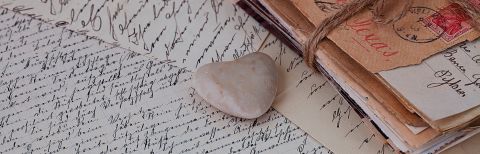
In deutschen Grundschulen und noch mehr in den weiterführenden Schulen liegt der Hauptfokus des handschriftlichen Schreibens in der Lesbarkeit der Schrift und der richtigen Rechtschreibung. Das ist unabdingbar, Lehrkräfte müssen lesen können, was die Schülerinnen und Schüler geschrieben haben, um den Inhalt und die Grammatik bewerten zu können. Die Rechtschreibung dient dazu, Wörter und Sätze eindeutig in ihrer Bedeutung zu machen, so sollen Doppeldeutigkeiten und Interpretationsspielräume ausgeschlossen werden.
Und wenn es beim Schreiben vor allem um Lesbarkeit und Rechtschreibung geht, so werden viele Schülerinnen und Schüler zu Recht fragen, warum sie dann nicht gleich mit dem Computer schreiben dürfen. Garantiert lesbar und eine Autokorrektur für die Rechtschreibung gibt es auch, also warum sollen sie noch mit der Hand schreiben? Die Handschrift hat aber noch weitere Aspekte: Es geht nicht immer nur darum, Inhalte zu vermitteln, sondern auch zu gestalten. Erinnern wir uns an die ersten Bücher, die in Klöstern von Mönchen in mühevoller Handarbeit abgeschrieben wurden, es gab nur einige wenige Exemplare und die waren überaus kunstvoll gestaltet.
Heute gelten sie als Kunstwerke. Briefe und Postkarten werden heute noch mit kleinen Randzeichnungen versehen und auch Bücher werden heute noch teilweise aufwendig illustriert. In diesen Bereichen verschwimmen auch bei uns Schrift und Kunst ineinander. Wer schreibt, gestaltet auch. Es ist durchaus möglich, Emotionen in der Schrift zu lesen. Ob ich einen Liebesbrief schreibe oder einen Einkaufszettel, würde man vermutlich auch an der Schrift erkennen: Meine Handschrift ändert sich, wenn ich schnell, energisch, nachdenklich oder wütend schreibe. Und manchmal werden uns Emotionen erst beim Schreiben bewusst, denn dann schreibt man in einem „Fluss“, das heißt, die Gedanken – positive wie negative – strömen vom Kopf wie von selbst über den Stift zum Papier. Das ist ein wichtiger Prozess der Selbsterkenntnis und -entwicklung. Vielleicht ist es auch einigen Schülerinnen und Schülern so ergangen, als sie ihre Briefe zum Thema „Mut“ geschrieben haben. Mut kann unterschiedliche Emotionen auslösen: Freude und Stolz, aber auch Angst und Wut.
Auch das Denken wird beim Schreiben gefördert. Einigen kommen die besten Ideen nachts, einigen unter der Dusche, aber ich glaube, beim Schreiben denkt es sich am besten, und das funktioniert beim Schreiben mit der Hand noch einmal wesentlich besser als beim Tippen am Computer. Der Schreibfluss regt zum Denken an, macht kreativ und einfallsreich. Handschrift ist spontaner als Tippen, man korrigiert weniger und oft, so sagt man ja, ist der erste Gedanke der beste.
Ich denke, das merkt man den vielen handschriftlichen Beiträgen zu diesem Wettbewerb einmal mehr an, da sie sowohl gestalterisch und emotional als auch inhaltlich besonders interessant sind.